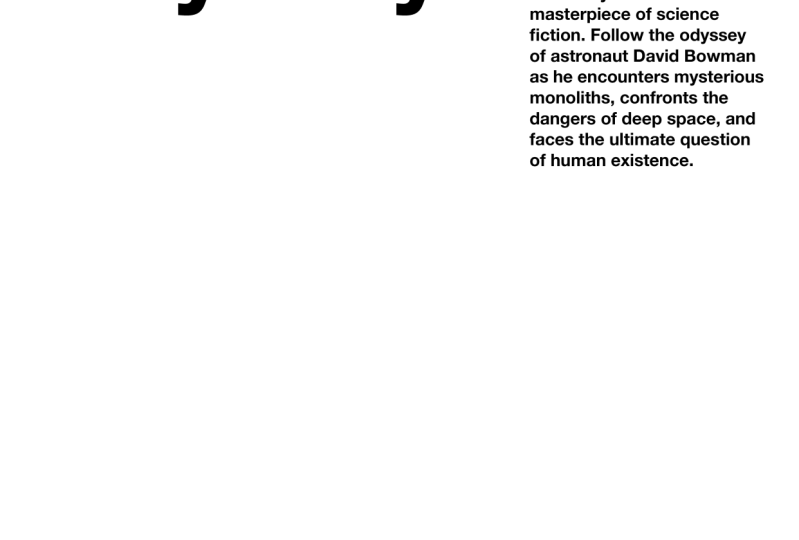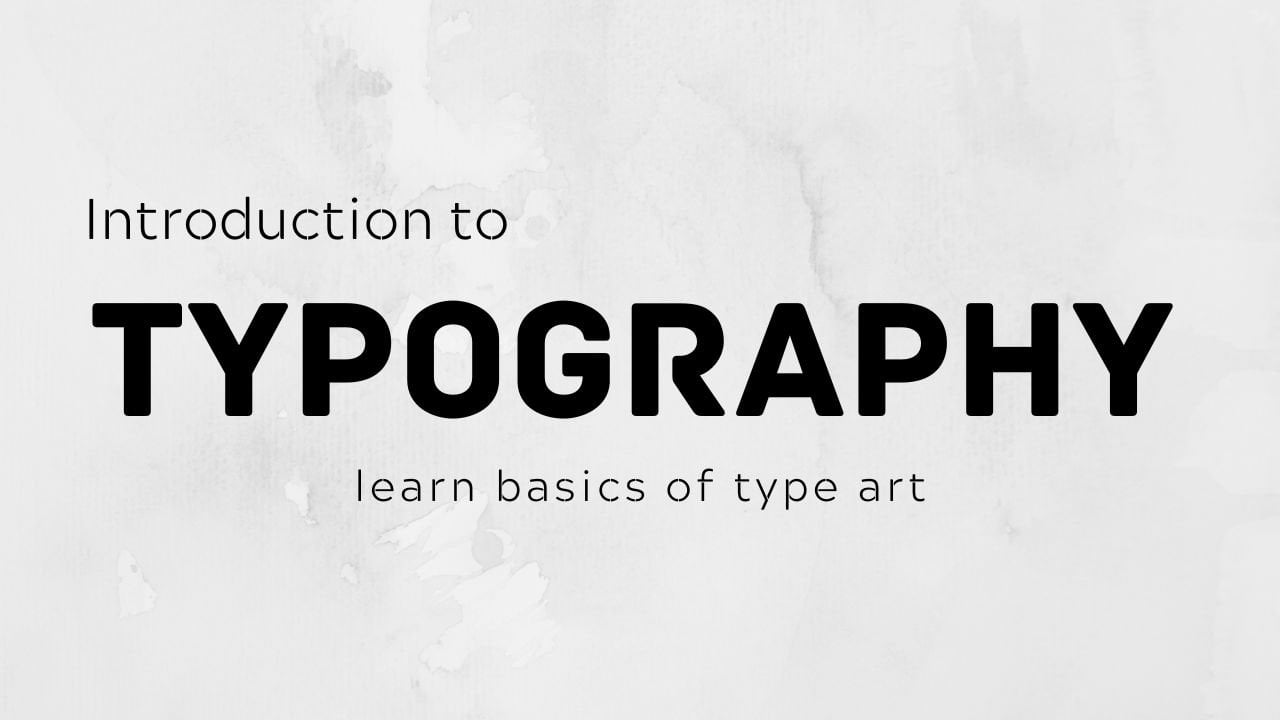
1. Einführung in die Typografie mp4: Hallo, mein Name ist Monica und ich bin Grafikdesignerin mit Sitz
in Großbritannien. Heute habe ich dir
beigebracht, was
Typografie ist, und dich damit
vertraut gemacht ? Was ist also Typbiografie? Biographie ist ein Stil
oder ein Erscheinungsbild von Text oder in menschlicher Sprache. Jeder Buchstabe, den wir sehen,
ist ein Seriengepäck. Es ist deine Brot-Einkaufsliste. Ist es deine Smartphone-App? Ist es Zeitung,
alles ist Topographie. Die Biographie kann sich auch
auf die Kunstform der Textgestaltung beziehen , die wir heute
lernen werden. Warum müssen wir
gut in Typografie sein? Das ist eine gute Frage. Styling von Übungen kann eine sehr wichtige Rolle
in Ihrem Text und den Informationen
spielen , die
Sie kommunizieren möchten. Beispielsweise
ist die Artikelüberschrift sowohl in großem Text, um den Leser über
den Inhalt des
Artikels zu
informieren , als auch um zu entscheiden, ob es sich um nützliche Informationen
handelt oder nicht.
2. 4 Serien: Was sind die Stile, was sind die Schriften,
die Schriften? Welches bevorzugst du? Es gibt zwei Hauptstile, die Schriftschalter,
Serifen und Sans-Serif. Fangen wir also zuerst
mit den Aufschlägen an. Es gibt eine Meinung und die Legende und vielleicht
stimmt sie, vielleicht auch nicht. Dieser Stil ist der allererste
Schriftstil, wie strukturierte Schriften. Wenn wir uns alte
römische Skulpturen, Monumente und
Schriften in den Steinen ansehen , können
wir sehen, dass es
diese Schlitze in den
Enden der Buchstaben gibt , wir Striche nennen. Also wurden sie ursprünglich hergestellt, der Legende nach wurden sie
hergestellt
, um Steinrisse zu verhindern. Und der Text wurde eingraviert oder auf andere Weise
in den Stein gehämmert. diesem Grund haben wir
Serifenschriften mit Strichen an den
Enden der Buchstaben. Aber kehren wir
zu unseren heutigen Tagen zurück. Was sind also die
gängigsten Serifenschriften? Ich kann Ihnen sagen, dass es Bodoni, Garamond, Baskerville
Times New Roman gibt. Ich glaube, Sie haben sie alle
irgendwo in dieser
Software gesehen , die Sie verwenden. Wofür? Für unsere Serifenschriften sind
Serifenschriften zunächst äußerst vielseitig. Sie können für
Überschriften, für Logos,
für das gesamte Branding und auch
für den Haupttext verwendet werden. Ein gutes Beispiel für die Verwendung einer
Reihe von Schriften ist Vogue. Vanity Fair Magazine, meiner Meinung nach, Serifenschriften vermitteln
den luxuriösen Eindruck. Und aufgrund der langen Geschichte
des Schriftstils werden
sie eher verwendet, um
luxuriöse Tradition und
etabliertes Branding auszudrücken . Dies ist jedoch keine Regel. Als nächstes folgt Sans Serifs.
3. San Serifs: Oh, die SDM-Knotenserie war erste und die Sensoren
werden danach ausgeführt. Ursprünglich war die
Idee,
die Striche zu entfernen und
nur einfache Buchstaben zu haben. Die gängigsten serifenlosen Schriften oder Aerial Gill Sans
für Dura Helvetica.
Ich glaube, Sie haben auch von allen
gehört. Wofür sind sie? San-Serif-Schriften sind
ebenfalls sehr vielseitig. Sie können
entweder für Überschriften,
für Logo-Variationen, überall für den
Haupttext verwendet werden. Grundsätzlich sind Sensitives auch für Luxus-Branding
beliebt. Es ist keine Regel, denn
nur Sklaven wären ein
Luxus-Branding-Tool. Der einzige Unterschied besteht jedoch darin, dass sie
sehr häufig ziemlich weit
voneinander entfernt sind. Aber ich kann auch,
das ist keine Reihe. Auch einige Dienste sorgen für erschwinglicheres Erscheinungsbild, z. B. während Vogue in Bodoni-Schrift und
Sonne in Franklin ist, können
Sie den
Unterschied zwischen
einem High-End-Modemagazin erkennen einem High-End-Modemagazin und Tageszeitung, die wir jeden Morgen
lesen.
4. Dekorativ: Eine weitere Gruppe von Schriften, über die ich mit Ihnen sprechen
möchte, die meiner Meinung nach
ebenfalls
sehr wichtig ist, sind deklarative Schriften. Hier sprechen wir über
Handschrift, Kalligrafie,
handgerenderte Schriften, schwarze Buchstaben und alles, was Sie sich vorstellen können, und alles, was Sie sich vorstellen können und Ihrer
integrierten Basis freien Lauf lassen. Aber Vorsicht vor diesem Start, diese stilistische Wahl wird
am besten in Maßen verwendet. Stellen Sie sich vor, es wird
ziemlich schwer zu
lesen sein , wenn es sich auf einer
Website oder einer App befindet. Bewahren Sie
sie also am besten für einen ganz
besonderen Anlass auf. Auch hier gilt nicht, dass
das Logo dekoriert werden muss, aber wenn Sie sich dafür entscheiden, ist es besser, die
entsprechenden Buchstaben im
Logo als
in einem Haupttext zu verwenden. Ich werde Ihnen
einige Beispiele für den übermäßigen Gebrauch deklarativer Texte geben. Und Sie können deutlich sehen
, was ich vorhabe. Siehst du, wie
schwierig es ist zu lesen? Ist es für
das Bauteil geeignet? Einige von ihnen, ja,
vielleicht. Manche von ihnen nicht. Vielleicht liegt es an Ihnen
als Designer, zu entscheiden.
5. Größe: weiterer sehr wichtiger Teil der Topographie ist die
Schriftgröße und das Gewicht. Und warum ist das so und was ist diese Schriftgröße, die in Punkten
gemessen wird. diesem Grund sehen wir PT in den meisten
von uns verwendeten Programmen. Sie stellen wahrscheinlich fest
, dass die neue Öffnung, jede Software, die Sie normalerweise verwenden, 12 Punkte die
Standardgröße ist. Es gibt Ihnen
sofort , wenn Sie
Ihr Projekt beginnen. Warum ist das so? Weil Größe 12
ideal ist, wenn Sie digital
arbeiten oder
Inhalte erstellen, Text für den digitalen Auftritt. Wenn Sie jedoch vorhaben, Ihre Arbeit
zu drucken, ist
es besser, ein
kleineres Format in Betracht zu ziehen , da
auf einem Blatt Papier eine Textgröße von 12 Punkten, viel
Glück, ein bisschen zu groß. Es ist auch sehr wichtig zu
erwähnen, dass die Textgröße als
Teil der Typografie, Kunst und Textgröße eine
große Rolle in der Hierarchie spielen kann. Einfach die wichtigsten
Worte zu sagen, wird Durst sein. Das heißt, sie sind die
wichtigsten Informationen.
6. Gewicht: Tippe warte, was ist das? Es ist im Grunde eine
Dicke der Buchstaben. Wie wir früher gesehen haben,
gibt es Optionen wie dünn, normal, zentriert,
fett, fett und schwarz. Es gibt mehr als das, aber das
sind die häufigsten. Sie können auch
eine große Rolle in der
Hierarchie der Texte spielen. Selbst wenn der Text die gleiche
Größe wie der Hauptteil hat, wird der
schwerere Typ zuerst bemerkt und es wird Ihre Kunst für
die Informationen viel einfacher leiten .
7. Zusammenfassung: Okay, also fasse jetzt kurz zusammen, was wir heute in
diesem Crashkurs gelernt haben. Es gibt zwei
Haupttypen von Schriften: Beruhigungsmittel und serifenlose Schriften. Sie können
in den
unterschiedlichsten Situationen eingesetzt werden und sind äußerst vielseitig. Bei den kooperativen Schriften handelt es sich alle anderen Schriften, die
im Grunde genommen korrelativ aussehen. Entweder handelt es sich um Kalligrafie,
Handschrift schwarze Schrift, handschriftliche
Schriften, Neuheit usw.,
und zwar am besten in einer minimalen
Textmenge, als ob
übermäßiger Gebrauch schwer lesbar und nicht lesbar sein kann. Ich betone, dass
der Text hier
eine höhere Bedeutung hat und dass er berechtigt ist. Aka, du musst
den Text so einstellen, dass du ihn leicht und übersichtlich lesen kannst und ein Kampf um
dein Auge oder deinen Verstand ist. Schrift, Gewicht,
Buchstabenstärke. Und es bestimmt auch die
Höhe und Wichtigkeit
der Informationen und
trägt zur Lesbarkeit bei. Wenn dein Text fett,
schwarz bis ins kleinste Detail ist , kann
es ziemlich schwer zu lesen sein, glaube
ich, nicht wahr? Ich hoffe, dass diese Kurzanleitung Ihnen
hilft, in die
Typografiekunst einzuführen und Ihnen den
Einstieg in Ihr erstes Projekt zu erleichtern.
8. Aufgabe: Okay, ich hätte
das fast vergessen, kurz bevor wir gehen, kurz bevor wir fertig sind, möchte
ich dich herausfordern. Geben Sie eine Entwurfsaufgabe. Ich habe viel nachgedacht. Es würde so viel Spaß machen, einen zu erstellen, und jeder würde Spaß daran haben, ihn solide
zu machen. Und nach ein
paar Überlegungen entschied
ich, dass es eine großartige Idee
wäre,
ein rein typografisches Poster zu erstellen ein rein typografisches Poster für Ihren Lieblingsfilm wirbt. Und wenn ich
rein typografisch sage, meine
ich wirklich, dass man
nur Schrift und Farbe verwenden kann. Keine Bilder, keine Illustrationen und nichts dergleichen. Übernimm nur die Macht von n. Und es wird eine Herausforderung
sein. Ich denke in einigen Fällen, in manchen Fällen
vielleicht nicht so sehr. Aber vergiss nicht
, dass die Regeln der Typografie immer noch gelten wenn du
ein Poster für den Film machst. Oh, du schreibst einen Brief
für deinen besten Freund. Vergessen Sie also nicht die
Hierarchie über der Schriftgröße, Schriftgewicht und der
Gesamtplatzierung auf
dem Blatt Papier. Also vergiss nicht,
Sie nicht zu überprüfen, ob das Kerning in Ordnung ist. Was ist eine Niere? Die Niere ist. Erzählen Sie das in